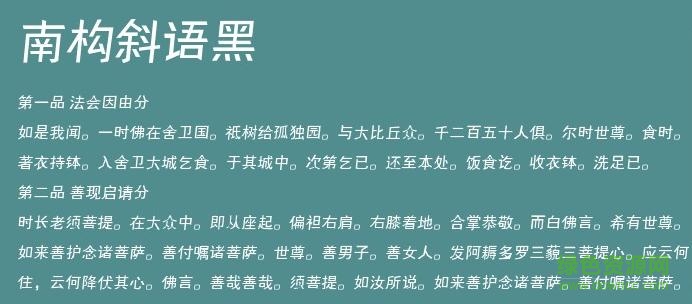
南構(gòu)斜語黑字體是南構(gòu)字體出品的黑體字體,筆畫稍微向右傾斜,自帶樂趣,橫平豎直、筆畫分明,傾斜帶來了一絲活潑,整體感極強(qiáng)。歡迎大家來綠色資源網(wǎng)下載使用!
南構(gòu)斜語黑字體,該字體菱角分明,筆畫錯落有致,藝術(shù)感強(qiáng),且整體效果非常出色。